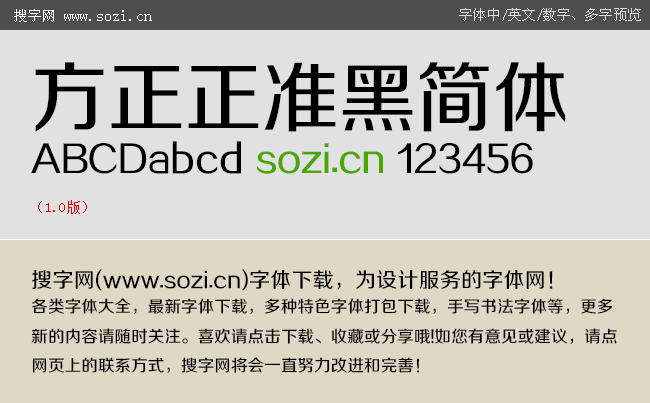
方正正準(zhǔn)黑簡體
搜字網(wǎng)提供一方正正準(zhǔn)黑簡體中文藝術(shù)字體下載,正黑體取傳統(tǒng)黑體結(jié)構(gòu),筆形全部采用平行、垂直與弧度的流線形設(shè)計,簡潔易識、美觀大方,具有個性,加之鏡像對稱的現(xiàn)代構(gòu)成形式,達(dá)到莊重與簡潔有機(jī)融合、設(shè)計感與閱讀功能兼?zhèn)涞淖罱K效果。適合書籍排版,報紙排版,海報設(shè)計,包裝設(shè)計等廣告設(shè)計場合應(yīng)用。